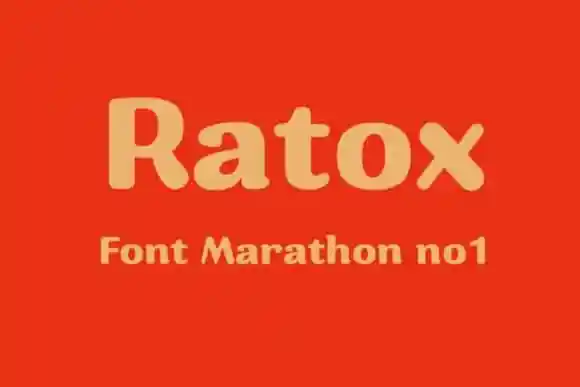
Ratox Sans Serif Font – Download Grátis
A Ratox Sans Serif é uma tipografia serifada vintage criada pela YTY Digital TypeFoundry. Inspirada nos jornais dos primeiros anos do século XX, essa fonte se destaca por suas bordas arredondadas e serifas com o formato de um ângulo suave, proporcionando um look alegre e elegante aos textos. Além disso, seu design é tão eficaz na resolução pequena que torna-a uma escolha ótima para blogs, eBooks, interfaces de usuário e até mesmo aplicativos. Com uma história rica em tempo passado, mas ainda relevante para a forma como vemos e nos comunicamos atualmente, a Ratox Sans Serif se destaca entre as fontes sans-serif graças aos seus detalhes meticulosamente cuidados que garantem tanto um look moderno quanto vintage.